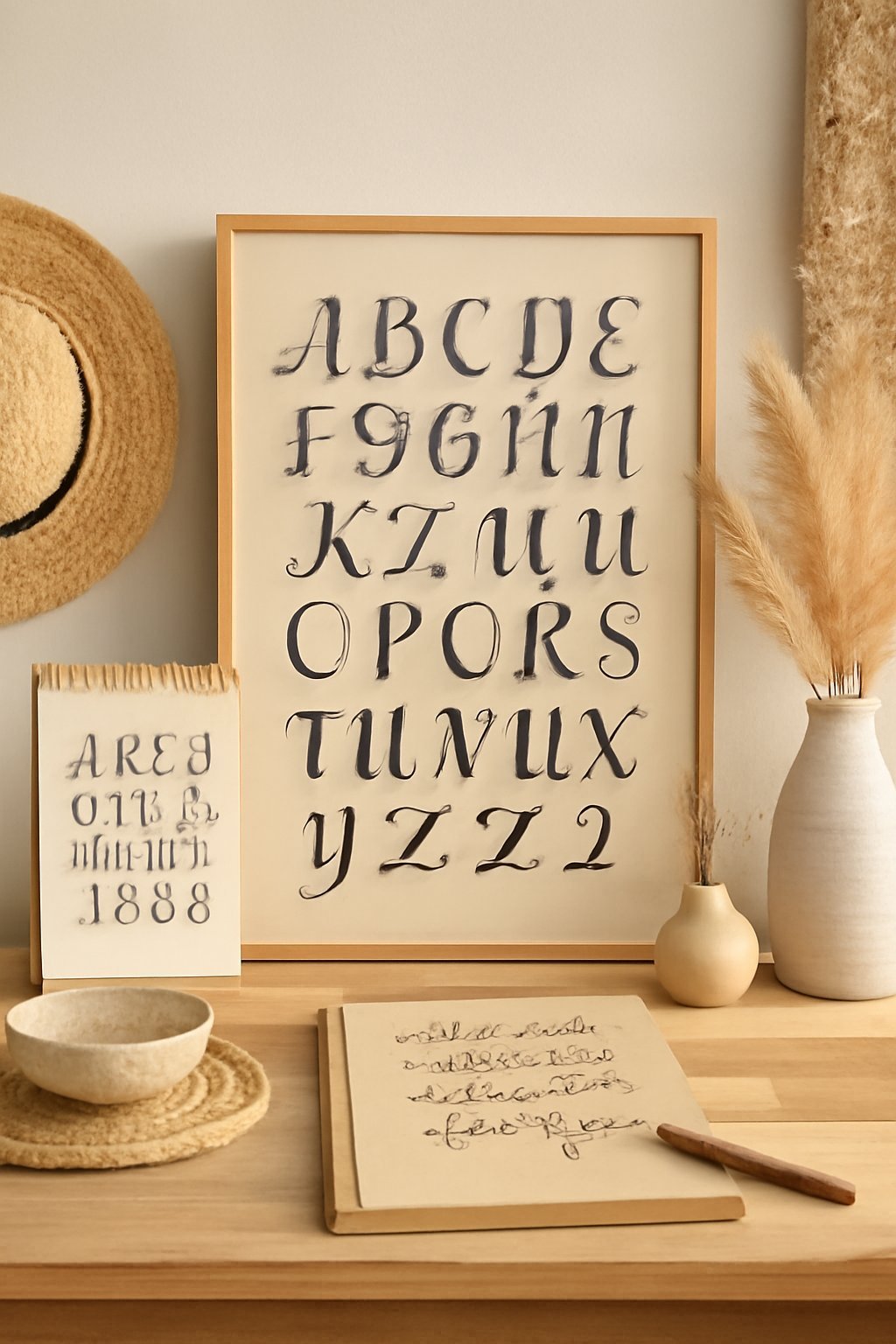
Handlettering Schriftarten Vorlagen: 12 kreative Ideen zum Selbermachen
Es gibt einen einfachen Trick, um deine persönlichen Notizen und Geschenke mit Handlettering Schriftarten Vorlagen zu veredeln. Diese Vorlagen bieten eine kreative Möglichkeit, deine Schriftkunst zu verbessern und eignen sich ideal für DIY-Enthusiasten sowie Bastler. Laut den Bewertungen und Foren ist Handlettering nicht nur eine entspannende Beschäftigung, sondern auch ein effektives Mittel, um alltägliche Dinge ein wenig besonderer zu machen. Ob du eine Einladung, ein persönliches Geschenk oder eine Notiz verschönern möchtest – die Möglichkeiten sind nahezu unbegrenzt. In der Recherche zeigen zahlreiche Tipps und Vorlagen, wie wichtig es ist, den richtigen Stil für dein Handlettering zu finden. Von verschnörkelten Schriftzügen bis hin zu schlichten, modernen Designs – die Auswahl ist riesig. Handlettering Schriftarten Vorlagen helfen dir, die perfekte Schriftart zu wählen und bieten eine Grundlage, auf der du kreativ aufbauen kannst. Viele Nutzerinnen berichten, dass das Experimentieren mit verschiedenen Stilen und Techniken nicht nur Spaß macht, sondern auch das eigene Geschick fördert. Im Folgenden findest du zwölf kreative Ideen zum Selbermachen, die dir helfen, mit Handlettering Schriftarten Vorlagen zu starten. Egal, ob du Anfänger oder bereits etwas erfahren bist, diese Inspirationen bieten dir eine wertvolle Grundlage und Anregungen, um deine schriftlichen Projekte zum Leben zu erwecken.
Warum Handlettering Schriftarten Vorlagen
Handlettering Schriftarten Vorlagen sind nicht nur eine praktische Hilfe, sondern auch eine inspirierende Möglichkeit, deiner Kreativität Ausdruck zu verleihen. Ursprünglich aus der Kalligrafie entstanden, hat sich Handlettering in den letzten Jahren zu einem beliebten Trend entwickelt. Ob für Einladungen, Geschenkanhänger oder persönliche Notizen — die Vielseitigkeit von Handlettering hat es ermöglicht, individuelle Akzente zu setzen und alltägliche Dinge in kleine Kunstwerke zu verwandeln. Bei der Auswahl von Vorlagen gibt es einige Dinge zu beachten. Du kannst zwischen verschiedenen Stilen wählen, von verschnörkelten und eleganten Schriften bis hin zu lässigeren und modernen Varianten. In den letzten Jahren haben sich auch digitale Vorlagen etabliert, die das Erstellen eigener Schriftarten erleichtern. Diese Vorlagen bieten dir nicht nur einen schnellen Einstieg, sondern helfen dir auch, verschiedene Techniken und Stile auszuprobieren. Besonders reizvoll ist die Möglichkeit, deine eigenen Schriftarten zu entwickeln, was es dir erlaubt, deiner persönlichen Handschrift eine besondere Note zu verleihen. Dabei kommt es auf Details an — die Form der Buchstaben, den Abstand und die Linie. Mit Handlettering Schriftarten Vorlagen kannst du experimentieren und herausfinden, was dir am besten gefällt. So wird Handlettering zu einem spannenden und kreativen Prozess, der dir hilft, deinen eigenen Stil zu entdecken und weiterzuentwickeln.
Handlettering Schriftarten Vorlagen: 12 kreative Ideen zum Selbermachen
1. Beginne mit dem Skizzenbuch und wähle eine leere Seite aus. Nutze das Lineal, um eine gerade Linie zu zeichnen, die dir als Basislinie für deine Buchstaben dient.
2. Nehme den Bleistift zur Hand und skizziere die Umrisse der Buchstaben, die du gestalten möchtest. Beginne mit einfachen Buchstaben und arbeite dich zu komplexeren Formen vor.
3. Sobald du mit den skizzierten Buchstaben zufrieden bist, nimm den Fineliner und ziehe die Umrisse nach.
4. Radier die Bleistiftlinien vorsichtig weg, nachdem die Tinte vollständig getrocknet ist.
5. Jetzt kannst du mit dem Ausmalen der Buchstaben beginnen. Wähle Farben, die gut harmonieren und deinen persönlichen Stil widerspiegeln.
6. Überlege dir, wie du deine Schriftarten verwenden möchtest. Du kannst sie für Karten, Geschenke oder Wanddekorationen nutzen.
7. Wenn du mehrere Vorlagen erstellt hast, scanne sie ein, um digitale Kopien zu erstellen. So kannst du deine Designs immer wieder verwenden oder anpassen.
8. Schließlich, sammle alle deine Vorlagen in einer Mappe oder einem Ordner, um sie ordentlich aufzubewahren.
Gelingtipps
1. Übe regelmäßig, um deine Fähigkeiten im Handlettering zu verbessern und flüssiger zu werden.
2. Halte deine Werkzeuge sauber, um ein optimales Ergebnis zu erzielen.
3. Experimentiere mit verschiedenen Schriftarten, um deinen eigenen Stil zu finden.
4. Nutze unterschiedliche Strichstärken, um mehr Dynamik in deine Buchstaben zu bringen.
5. Beginne mit einfachen Buchstaben und steigere die Komplexität, um Frustration zu vermeiden.
Variationsideen
• Kalligrafie: Verwende spezielle Kalligrafiefedern für einen eleganteren Schriftzug.
• Aquarell-Designs: Integriere Aquarellfarben, um einen kreativen Hintergrund zu schaffen.
• Digitale Vorlagen: Nutze Grafikprogramme, um digitale Schriftarten zu erstellen.
Schritt 1
Beginne mit dem Skizzenbuch und wähle eine leere Seite aus. Nutze das Lineal, um eine gerade Linie zu zeichnen, die dir als Basislinie für deine Buchstaben dient. Achte darauf, dass die Linie leicht und nicht zu dunkel ist, damit sie später leicht radierbar ist. Dies gibt dir eine Orientierung für die Höhe und Ausrichtung deiner Buchstaben.
Schritt 2
Nehme den Bleistift zur Hand und skizziere die Umrisse der Buchstaben, die du gestalten möchtest. Beginne mit einfachen Buchstaben und arbeite dich zu komplexeren Formen vor. Halte die Striche leicht, sodass du sie später anpassen kannst. Achte darauf, dass die Buchstaben gleichmäßig sind und eine harmonische Schriftart entsteht.